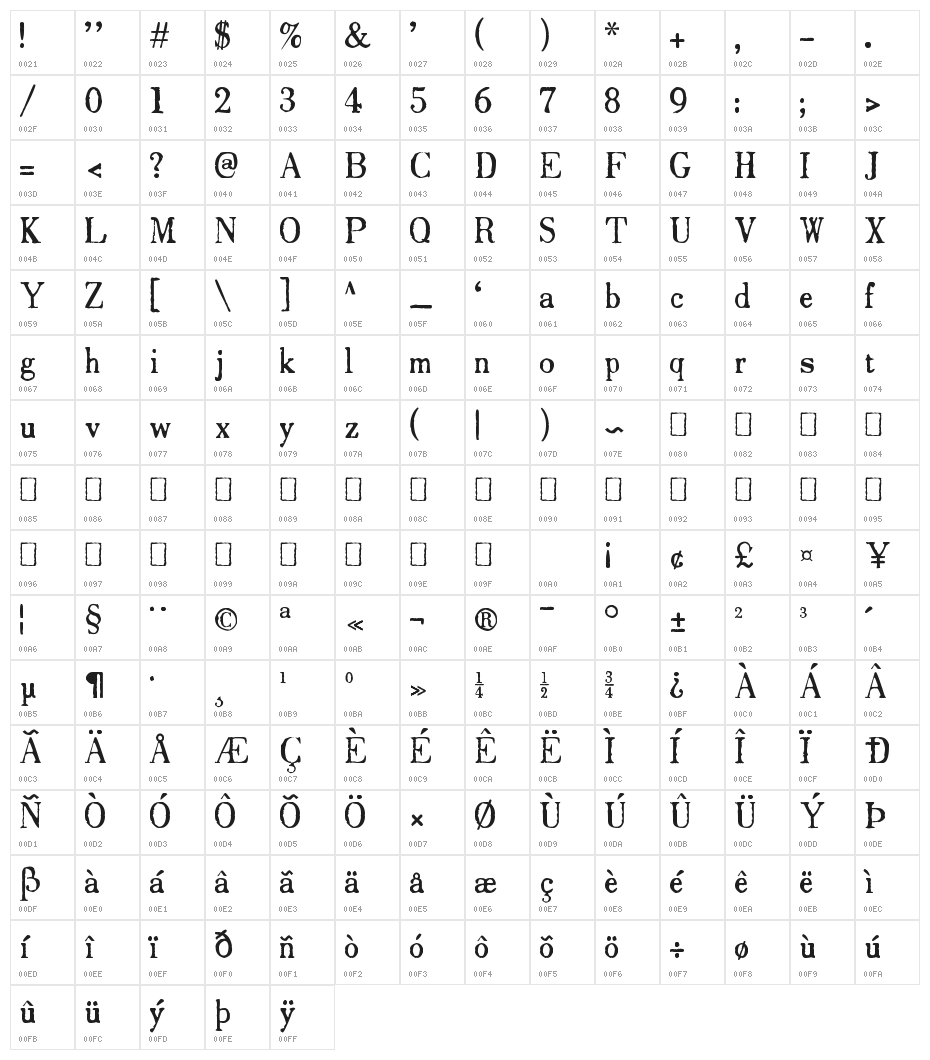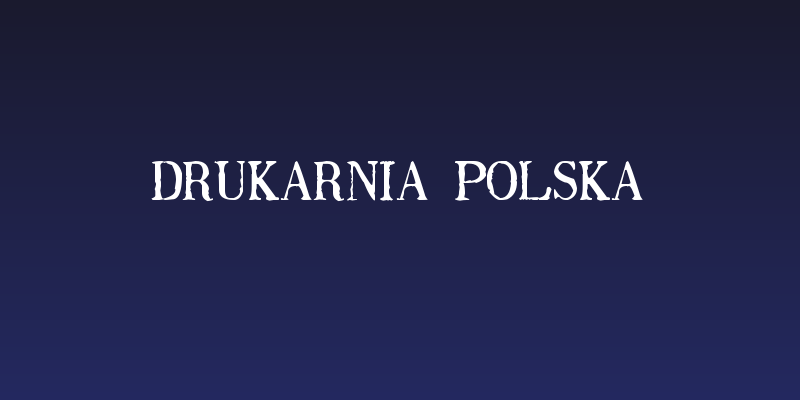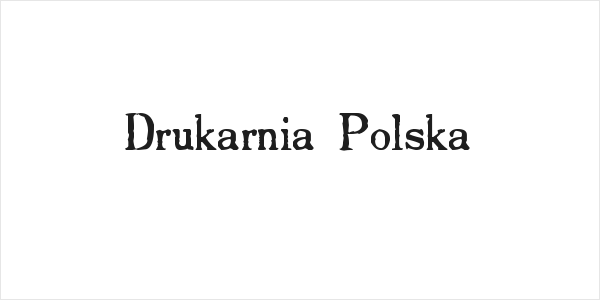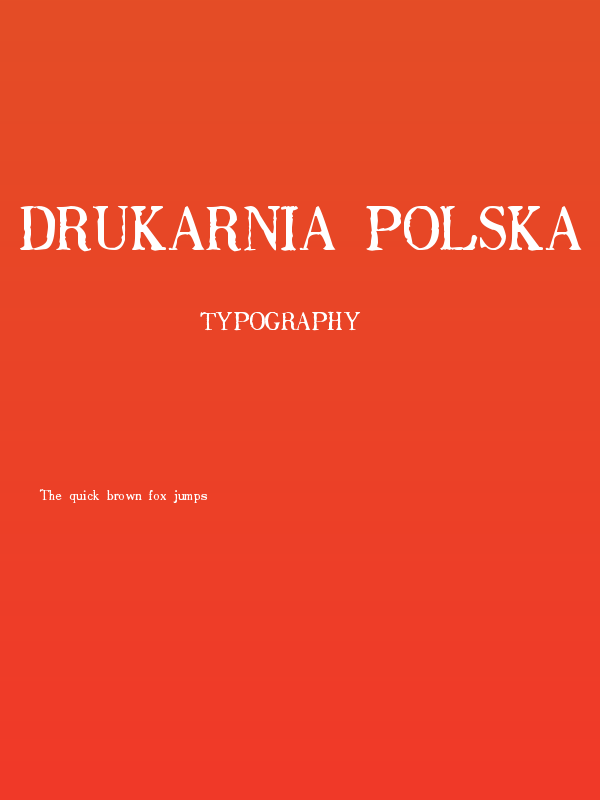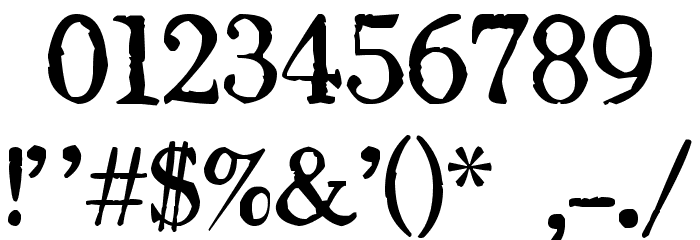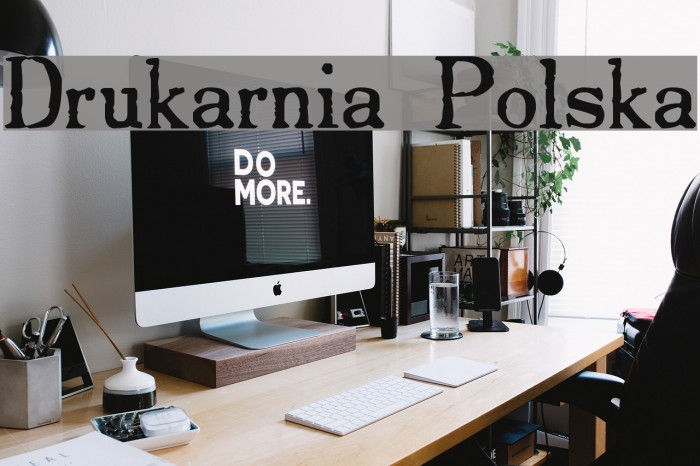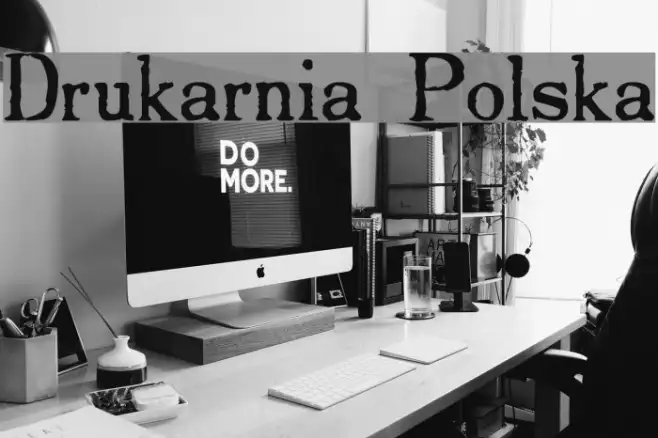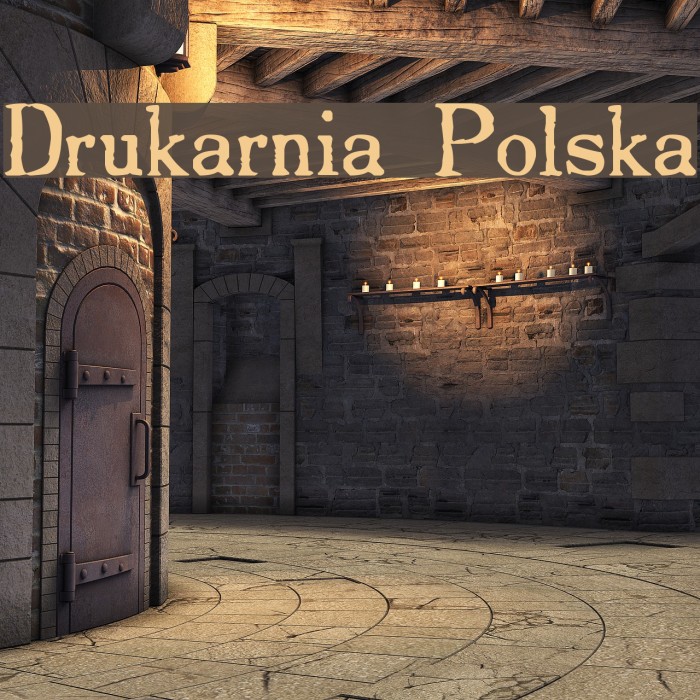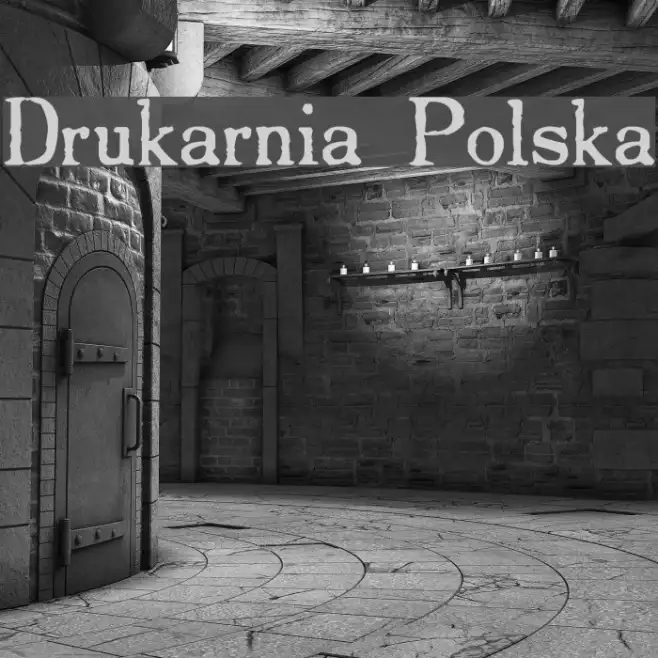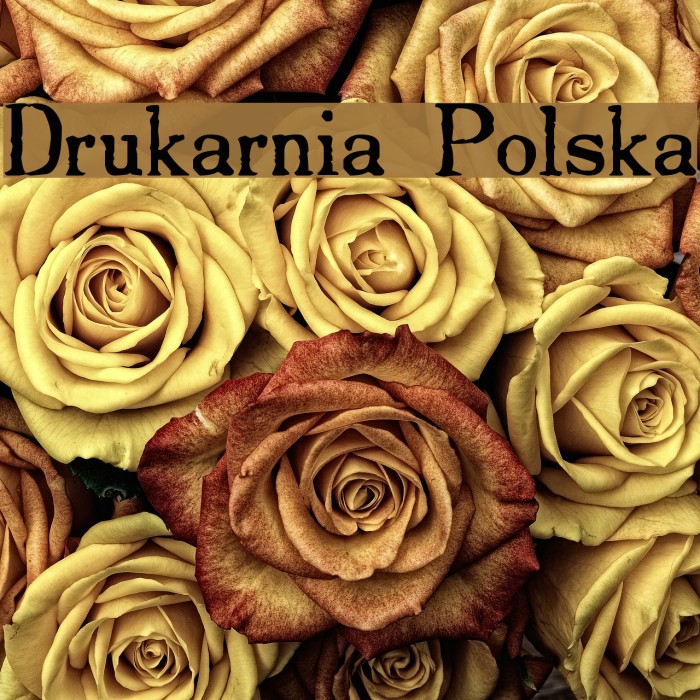
Drukarnia Polska Font
✎ Distorted Eroded
| Progetti proposti | Ideal for projects that require a historical or rustic touch, such as vintage posters, book covers, branding for artisanal products, or themed event invitations. |